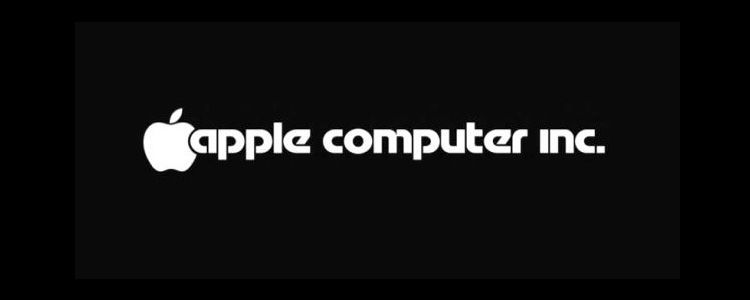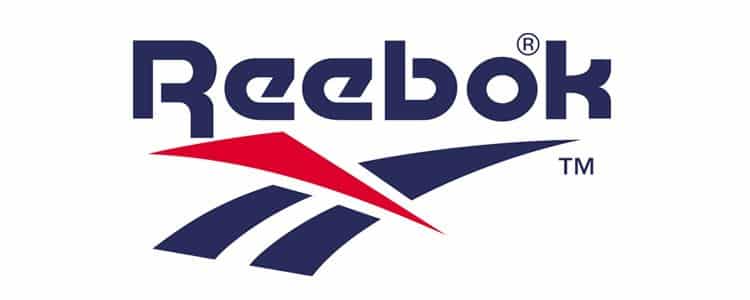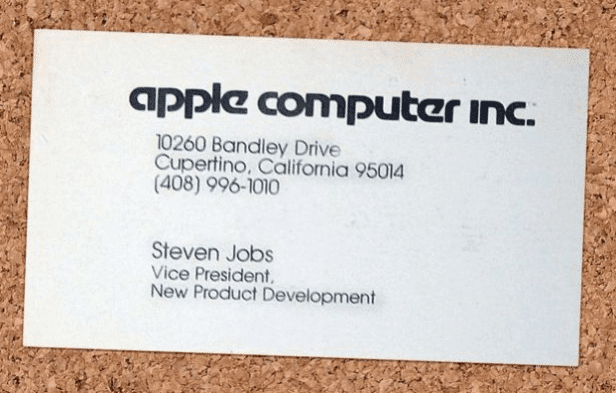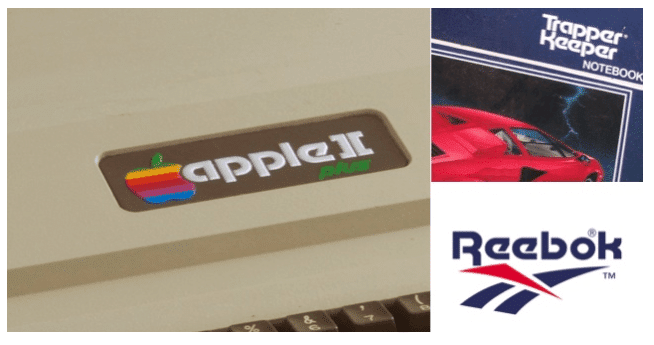
La tipografía de moda en los años 80
La tipografía dominante en los años 80 fue la Motter Tektura, creada en 1975 por el diseñador australiano Othmar Motter, quien falleció en 2010.
Grandes marcas dominantes en los años 80 como Apple, Reebok y Trapper Keeper utilizaron esta tipografía futurista para sus logotipos y comunicaciones corporativas.
De hecho, Motter Tektura jugó un papel fundamental en la evolución de la identidad corporativa de Apple. Ahora ya sabéis por qué la manzana de esta marca tiene un mordisco en su lado derecho.
Steve Jobs usó esta tipografía también en sus tarjetas de vista en el año 1979:
Los motivos por los que la Motter Tektura no ha llegado a ser tan popular como la Helvética se pueden deber a que no hay una versión digital autorizada de esta tipografía. En 1975, o incluso en 1979, algunas tipografías se diseñaban todavía de forma analógica. Si añadimos que su creador no se preocupó demasiado por darle un impulso a su propia tipografía ya que pasó a diseñar logotipos tenemos las razones por las que la tipografía no ha sobrevivido este tiempo.
Esperemos que se ponga de moda otra vez.